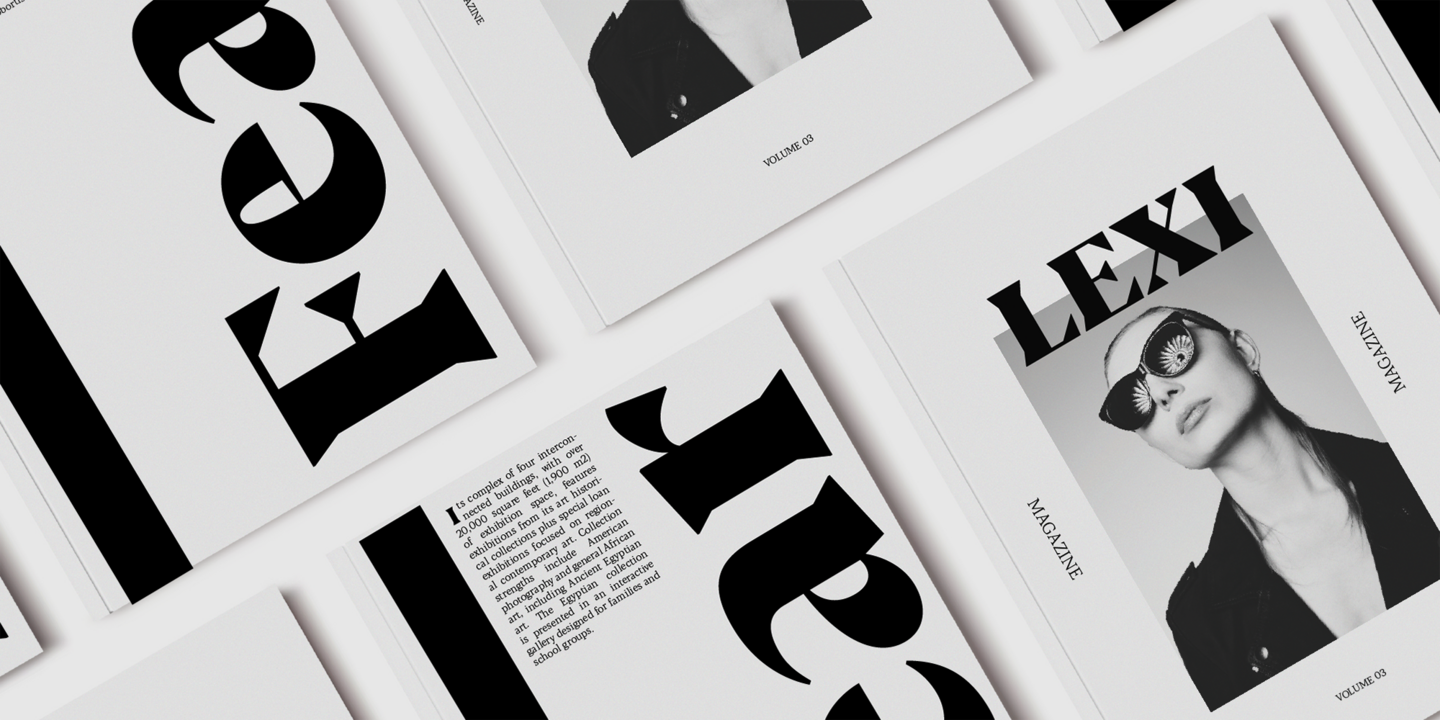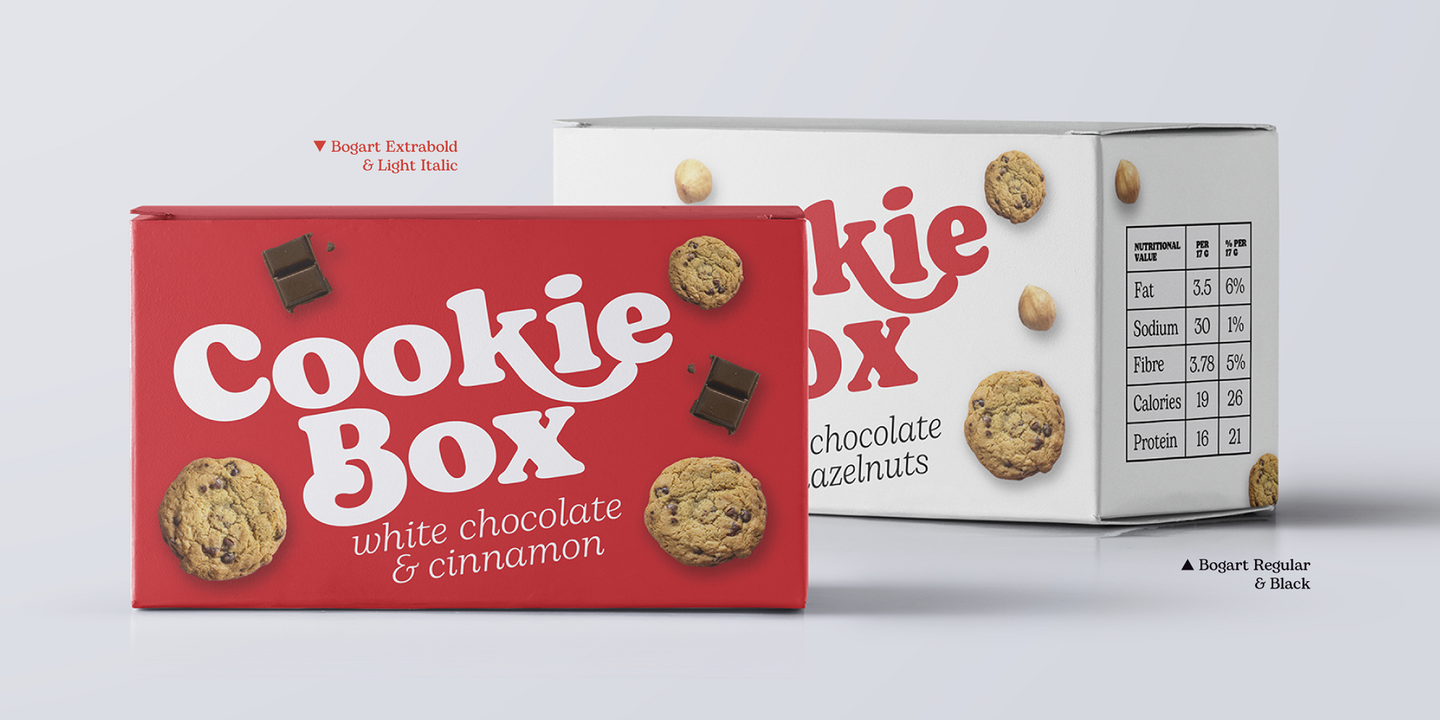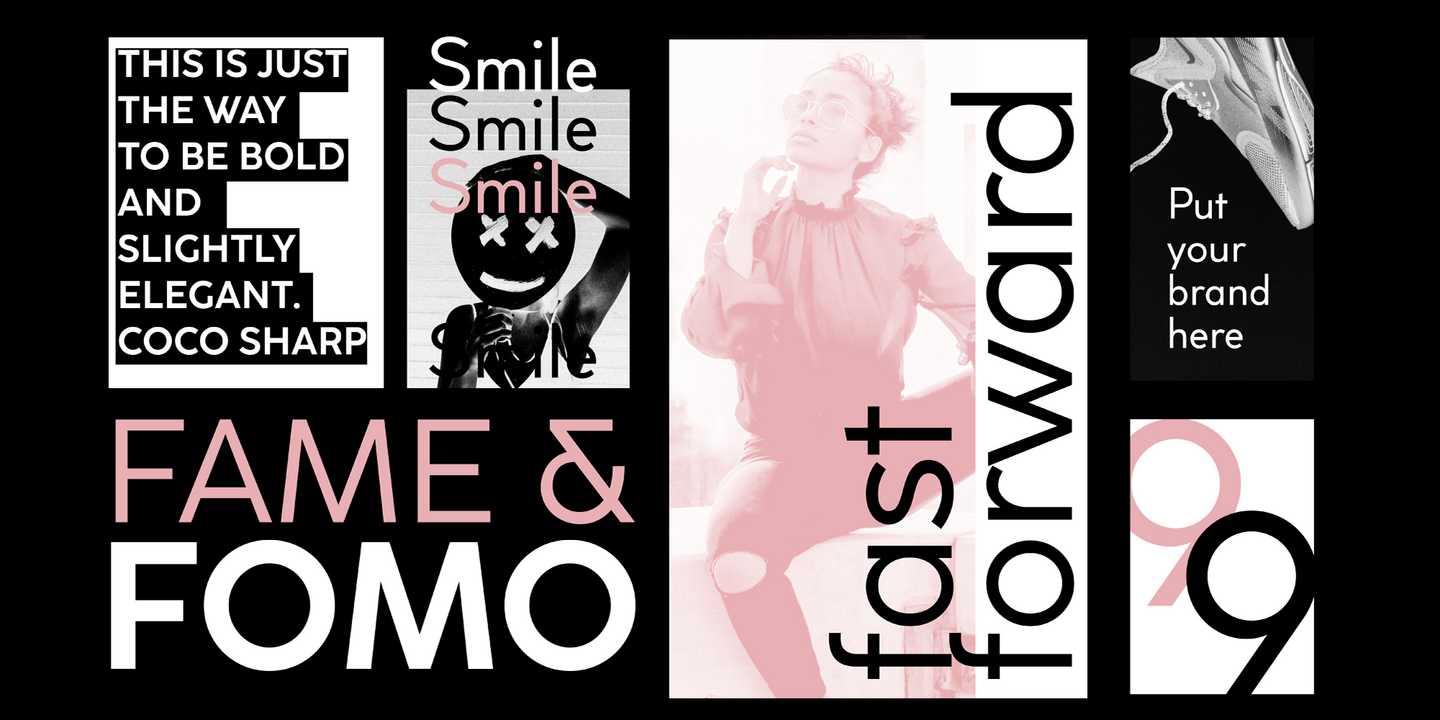
Fuentes de Zetafonts.
Orgullosos de criar zorros marrones rápidos desde 2001. Zetafonts diseña finamente tipos de letra de alta calidad para minoristas y ofrece servicios de diseño personalizados fuente para clientes comerciales e institucionales.
Tipos de letra populares de Zetafonts
Blacker se desarrolló como una versión del estilo definido como género de "gracias malignas": tipos de letra con alto contraste, proporciones de gracias de estilo antiguo o moderno y gracias triangulares afiladas como cuchillas. Debido al alto contraste del diseño, que recuerda ligeramente a los tipos didone, Blacker se ha desarrollado en dos subfamilias ópticas (pantalla y texto), además de otras dos familias de variantes condensadas y tres variantes de títulos sólo en mayúsculas. Cada una de estas variantes se ha desarrollado en seis pesos para un total de 69 estilos que cubren una amplia gama de usos editoriales y publicitarios.
La peculiaridad de Coco Sharp reside en la amplia gama de alturas x que ofrece al usuario, con una versión variable y cinco subfamilias graduadas que permiten a los diseñadores controlar con precisión la legibilidad del texto y el uso del espacio. Los 60 pesos de Coco Sharp incluyen un conjunto completo de funciones de tipo abierto que permiten una composición tipográfica impecable. Utilice Coco Sharp desde el primer momento como una sólida familia de trabajo o disfrute descubriendo las ilimitadas posibilidades de sus más de 2.000 glifos latinos, cirílicos y griegos que cubren más de 200 idiomas de todo el mundo.
Sensual pero afilada, Erotique habla el lenguaje de las burlas y el amor no correspondido. Diseñado para su uso en pantalla, este tipo de letra con gracias de alto contraste está listo para ocupar el centro del escenario en proyectos en los que se requiera una elegancia sutil y un toque agresivo. Para la creación de marcas, se combina con los ornamentos Erotique, lo que permite crear llamativos diseños de envases, digitales y de ambiente. Para uso editorial, puede añadir una aguda sensualidad a logotipos y títulos gracias a una impresionante gama de glifos alternativos, sutiles ligaduras y un conjunto de florones en forma de látigo. Si le gustan los tipos de letra, le advertimos: Erotique podría ser su atracción fatal.
Bogart se ha diseñado como un homenaje al aspecto icónico de las antiguas fuentes gordas de bajo contraste, como Cooper Black y Goudy Heavy Face. Los nueve pesos de Bogart, así como las formas de cursiva verdadera a juego, presentan un conjunto de caracteres ampliado de más de 1.600 glifos, que cubren 219 idiomas con alfabetos latino, cirílico y griego, y cuentan con un completo conjunto de características Open Type. Para añadir flexibilidad al uso editorial, se añadió a la familia un conjunto de nueve pesos Bogart Alternate orientado al texto, que mantiene el diseño más similar a su modelo moderno de estilo antiguo y permite una gama de pesos medios de gran legibilidad.
En el abarrotado panorama de los tipos de letra grotescos contemporáneos, todos ellos encaminados a la cruda perfección geométrica, Stinger destaca por sus atrevidas elecciones y su fuerte personalidad. Stinger es una superfamilia con cuatro anchos, cada uno de ellos en cinco pesos diferentes. Desde los terminales inspirados en la caligrafía de los pesos finos hasta el enfoque escultural preparado para logotipos de los pesos pesados, cada variante consigue un aspecto llamativo sin olvidar las lecciones de legibilidad y flexibilidad de los clásicos modernos de contraste inverso.
Zetafonts crea tipos de letra significativos con una clara "situación de uso" y una fuerte "actitud de resolución de problemas". Su objetivo es proporcionar herramientas de diseño finamente elaboradas e innovadoras, pero sólidas, a diseñadores gráficos, directores artísticos y gestores de marcas de todo el mundo. La actividad de Zetafonts se orienta también hacia la promoción de la cultura ypográfica mediante la organización de iniciativas educativas, charlas y cursos.
Socio y Director de Proyectos
Cosimo Lorenzo Pancini
Cosimo compró su primer tipo de letra, un Arnold Boecklin letraset transfer, cuando tenía nueve años. Desde entonces no ha dejado de jugar con las letras, tanto escritas como dibujadas, trabajando como diseñador tipográfico, profesor de artes visuales y director artístico para medios impresos, digitales y de vídeo. Ha diseñado más de cincuenta familias tipográficas para la fundición Zetafonts, que fundó junto con Debora Manetti y Francesco Canovaro. Entre sus tipografías se incluyen Cocogoose, Blacker (seleccionada por Myfonts como una de las mejores nuevas familias de 2019), Monterchi (premio de tipografía CA 2020, Myfonts hidden gem 2019) y Stinger (premio de tipografía CA 2021). Vive en Florencia con su mujer, un gato llamado Bodoni y demasiados libros.
Socio y Director Creativo
Francesco Canovaro
Francesco ha encontrado en el diseño visual y la tipografía la evolución natural de sus estudios de pintura y programación informática. Con Debora Manetti y Cosimo Lorenzo Pancini fundó la agencia de branding transmedia Kmzero y la fundición tipográfica digital Zetafonts, sello bajo el que ha diseñado más de cuarenta familias tipográficas e innumerables personalizaciones fuentes. Entre sus tipografías se incluyen Aquawax, Heading (Bestseller de los Winter Type Games 2017 en Myfonts.com), Blacker (seleccionada por Myfonts.com entre las Mejores nuevas familias de 2019), Kitsch (seleccionada por Fontspring.com entre las Mejores fuentes de 2019). Tan temido como querido por sus alumnos en los cursos de dirección creativa y tipografía, se le ve a menudo en conferencias tipográficas escuchando charlas mientras crea nuevos tipos de letra en su portátil. Vive en Florencia con su mujer Debora y dos hijos cuyos nombres terminan en consonante.
Director de socios y nuevos negocios
Debora Manetti
Debora creció en la Toscana y pronto siguió los pasos artísticos de su padre, pintor y polímata. Viéndole escribir a mano todo el Infierno de Dante, heredó su amor por la caligrafía y la tipografía, una pasión que más tarde utilizó para impulsar su carrera como directora de arte, diseñadora visual y estratega de marca. Le encanta diseñar tipos de letra inspirados en la tipografía vernácula, que la hace sonreír por su espontaneidad, a menudo torpe pero genuina. También ha diseñado algunos manuscritos personalizados fuentes para proyectos de marca galardonados. Junto con Francesco Canovaro y Cosimo Lorenzo Pancini, es cofundadora de la agencia de branding Kmzero y de Ligature, una empresa centrada en la cultura del diseño tipográfico (Zetafonts / Italiantype / Fontmood).
Cada día recibe diferentes estímulos que le permiten tener una visión de 360 grados de su trabajo como diseñadora: siguiendo su instinto, consigue plasmar sus intuiciones en una delicada armonía entre puntos.